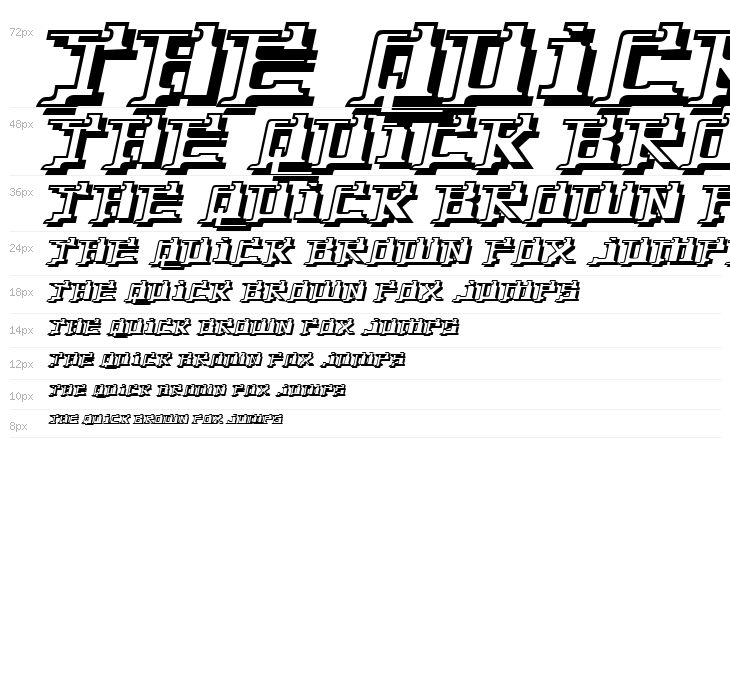
Yytrium-Regular Font
| Proiecte propuse | Ideal for video game titles, tech-related branding, posters, and any project needing a modern, digital look. |